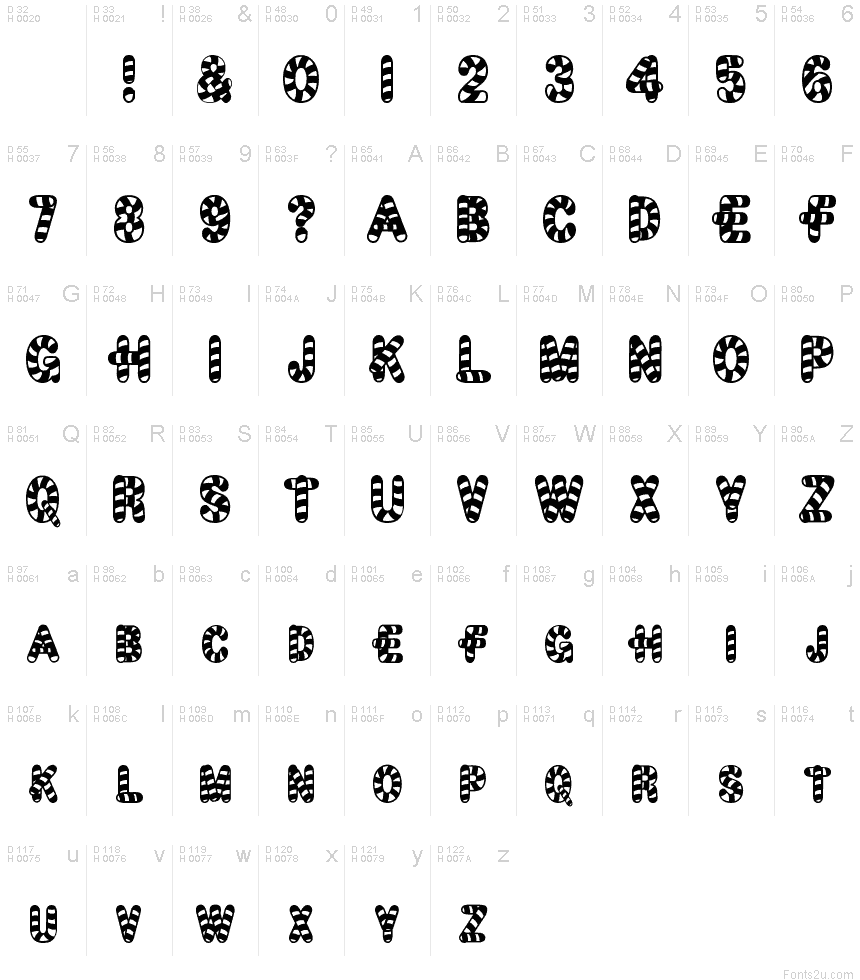
خط CandyTime من House of Lime هو خط عرض كرتوني مجاني يحول كل كلمة إلى كومة من عصي الحلوى المخططة. تلتف الحروف العريضة والمستديرة بمنحنيات سكرية وخطوط بيضاء سميكة، مما يمنح العناوين طابعاً مرحاً يكاد يكون قابلاً للأكل - تماماً مثل لافتة متجر حلوى مرسومة بعرق السوس والزينة. الإيقاع العام للخط مفعم بالحيوية والكثافة، بحيث تبدو حتى الكلمات القصيرة ممتلئة واحتفالية.
باستخدام CandyTime، يمكنك تصميم دعوات لحفلات الأطفال، وشعارات متاجر الحلوى، وملصقات الأعياد، وعناوين الألعاب، ولوحات الفصول الدراسية، وصور مصغرة لمقاطع يوتيوب للجمهور الشاب. يعمل هذا الخط المجاني بشكل أفضل كعنوان كبير وجذاب، بينما يفضل استخدام خط بلا زوائد (sans serif) بسيط ومستدير بحجم أصغر للنصوص الجانبية للحفاظ على الوضوح وسهولة القراءة بجانب هذا التصميم المليء بالحيوية.